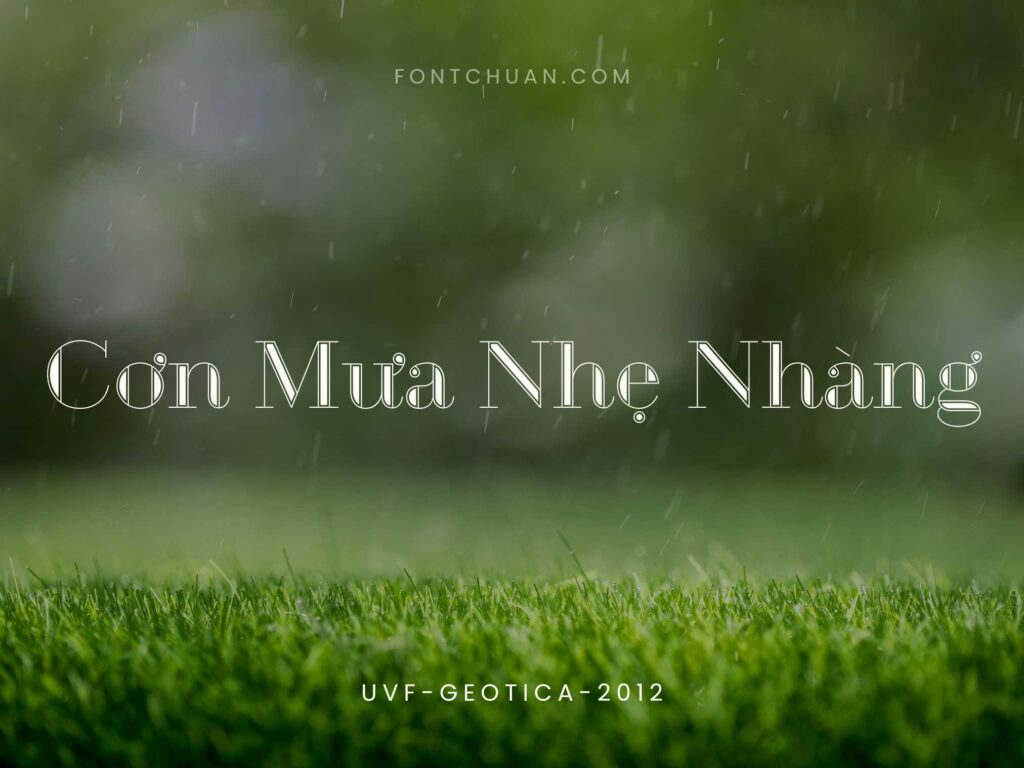
UVF Geotica 2012 là một font chữ serif trang trí độc đáo, mang phong cách cổ điển với các đường nét mềm mại và tinh tế. Font này tạo cảm giác sang trọng và lịch lãm, rất phù hợp cho các thiết kế như tiêu đề, logo, bao bì sản phẩm cao cấp và các ấn phẩm in ấn nghệ thuật. Với độ thẩm mỹ cao và khả năng ứng dụng rộng rãi, UVF Geotica 2012 là lựa chọn lý tưởng cho các dự án thiết kế mang đậm dấu ấn nghệ thuật.
Font này được sưu tầm và đăng bởi thành viên của Font Chuẩn. UVF Geotica 2012 hỗ trợ đầy đủ các ký tự tiếng Việt, đảm bảo tính ứng dụng cao trong nhiều dự án thiết kế. Ngoài ra, font còn hỗ trợ nhiều ngôn ngữ khác, giúp mở rộng phạm vi sử dụng trong thiết kế quốc tế.